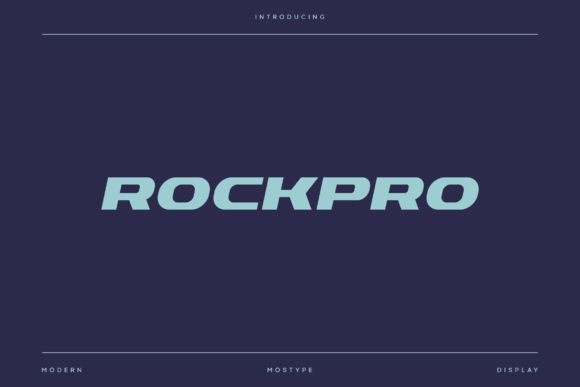
Rockpro
Rockproのような高品質の素材をお探しの場合、このプレミアムパッケージはクリエイティブなプロジェクトに素晴らしい選択です。
精密に作られたRockproは、クリーンなベクター、滑らかなタイポグラフィ、そして安心のための商用ライセンスを提供します。
POD(オンデマンド印刷)製品、結婚式の招待状、またはソーシャルメディアのグラフィックを作成している場合でも、Rockproは理想的です。